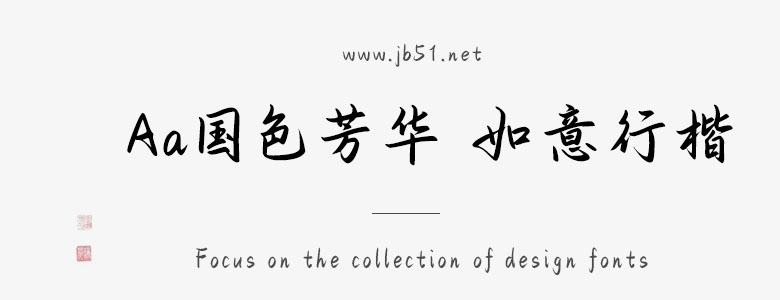
Aa國(guó)色芳華 如意行楷,字體筆觸適中,端正優(yōu)美,具有很好的視覺(jué)感,適合應(yīng)用于藝術(shù)設(shè)計(jì)、平面宣傳設(shè)計(jì)、網(wǎng)頁(yè)設(shè)計(jì),書(shū)法字帖等領(lǐng)域。有需要的朋友快來(lái)本站下載使用吧。